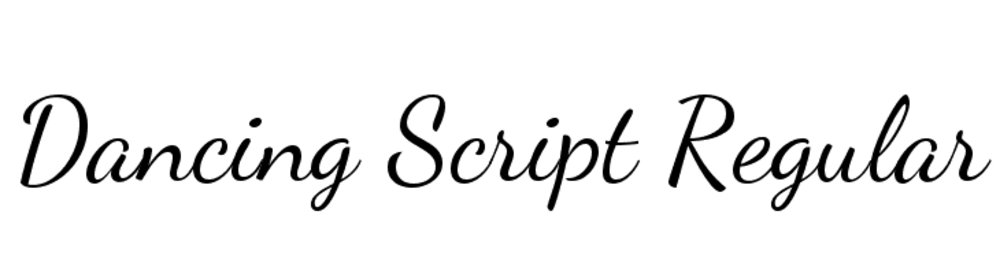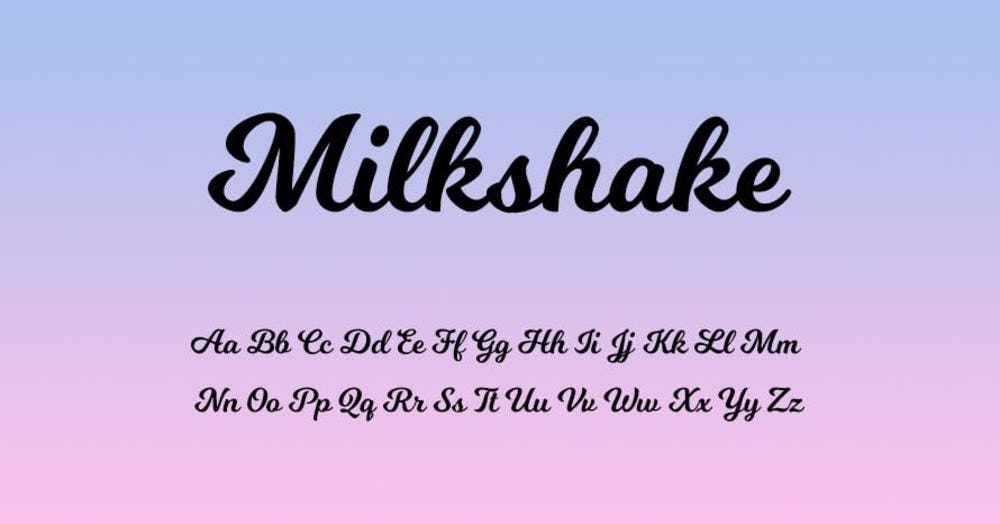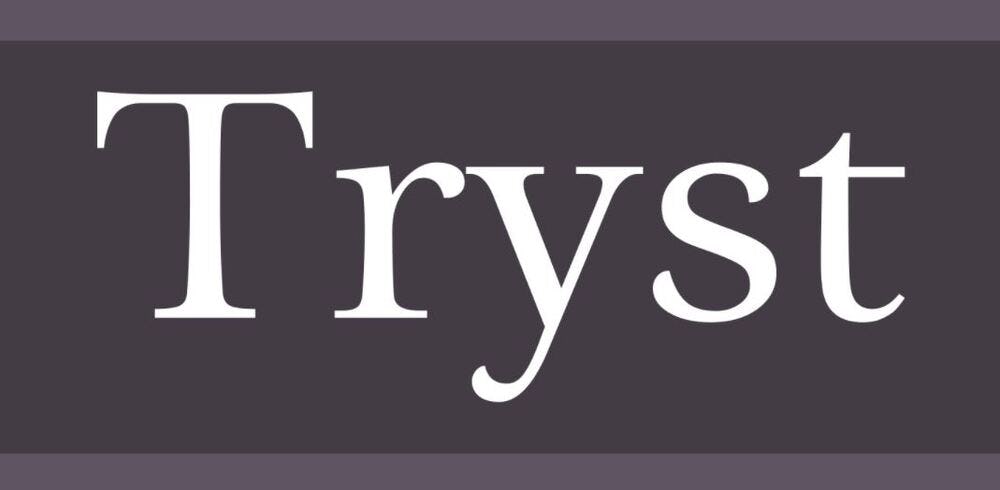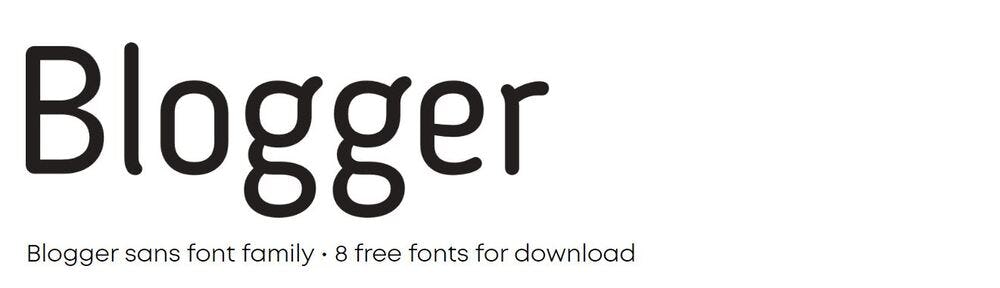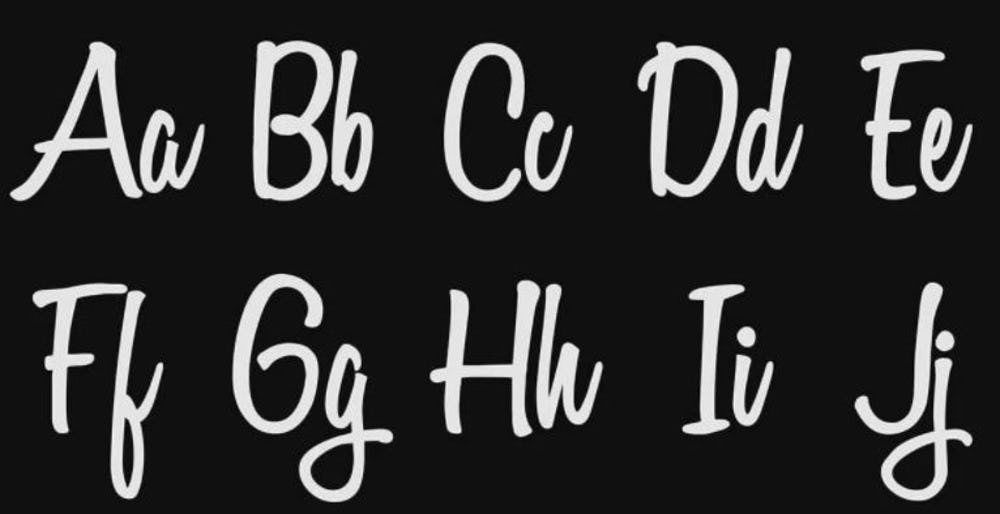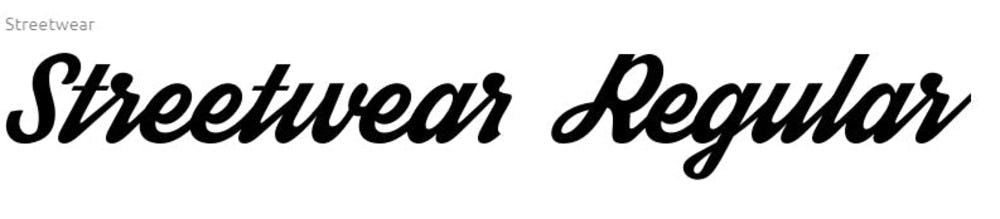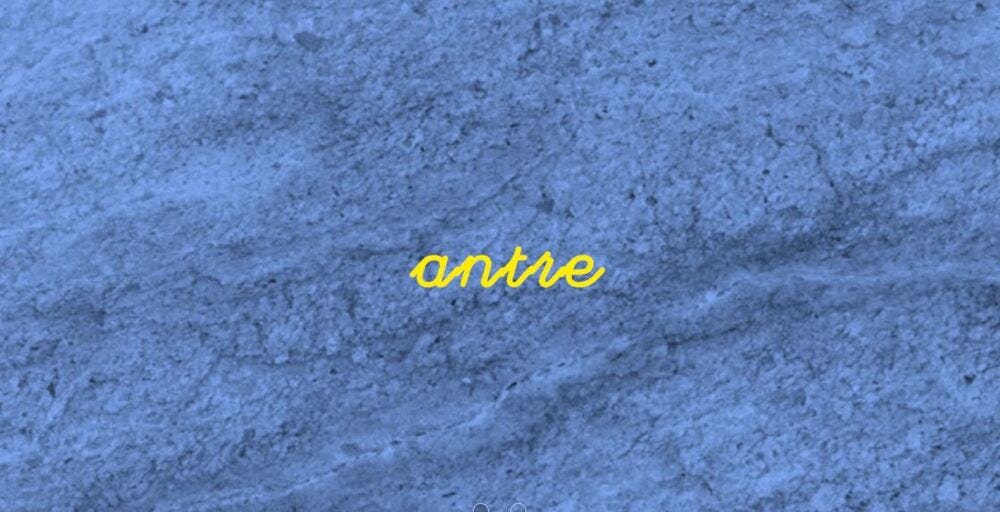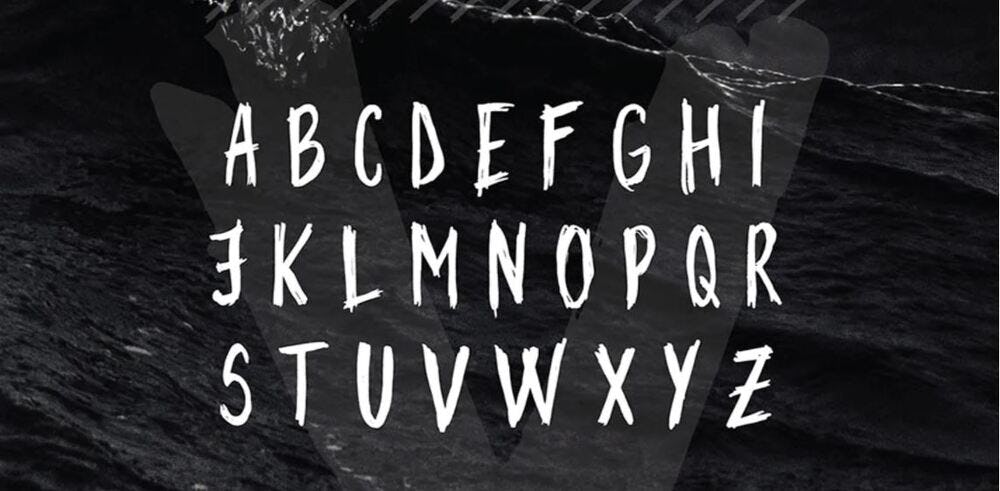
¿Buscas una tipografía para apuntes que te ahorre tiempo y se vea bien? ¿Estás cansado de ver las mismas letras para apuntes en Word o Powerpoint cada vez que haces un proyecto para la universidad o para el trabajo? Si bien al usar la tecnología ya no tenemos problemas para entender nuestras notas, la mayoría de fuentes no suelen ser tan vistosas.
Según la Escuela de la Memoria, organización enfocada en el desarrollo de la memoria de alta competición, la toma de apuntes nos ayuda a recordar mejor la información y estimula nuestras capacidades perceptivas e intelectuales. Sin embargo, por más que sea una actividad muy beneficiosa para ti, no podrás disfrutarla si no te sientes motivado a hacerlo.
Aquí entran en acción las tipografías para apuntes que hemos recopilado para ti, pues cada una hará que te enamores del proceso de tomar notas para que, cuando estés a cargo de la redacción de los puntos claves de algún proyecto o simplemente quieras anotar tu agenda de la semana, disfrutes cada segundo.
Recomendaciones para elegir la tipografía para apuntes ideal
Antes de que puedas descargar todas las tipografías para apuntes que hemos recopilado para ti, queremos compartir contigo algunas pautas que te ayudarán a escoger las fonts para apuntes que más te convienen.
Para ello, debes tener en cuenta que, si vas a utilizar una tipografía para apuntes para elaborar documentos, presentaciones animadas o simplemente para tomar notas, según Hubspot, lo mejor es evitar tipografías que tengan mucho diseño porque pueden confundir a quién tenga que leer el documento.
Si bien a todos nos gusta tener estilo, en la tipografía para apuntes debe primar, antes que nada, la legibilidad. La idea es que entiendas tus apuntes al primer vistazo y no tengas que detenerte para entender qué es lo que escribiste, pues, de lo contrario, tus apuntes perderían su misión principal: ayudarte a ahorrar tiempo.
Pero, tranquilo, esto no quiere decir que tengas que sacrificar tu buen gusto para utilizar letras que sean entendibles. En este artículo, encontrarás tipos de letra para apuntes que mezclan estilo y legibilidad, así que, finalmente, todo dependerá de tus gustos.
Tipografía para apuntes bonitos
Comenzamos nuestra lista de tipografías para apuntes con más de 10 alternativas que te cautivarán al instante por sus formas y estilos. Como te comentamos antes, si bien las letras para apuntes deben ser legibles, esto no quiere decir que deban ser aburridas.
1. Astron
Tipografía para apuntes futuristas
Si te gusta la onda gaming o futurista, este tipo de letra para apuntes es el indicado para ti. Si bien tiene un estilo particular, destaca por su gran legibilidad, así que no es para nada descabellado que las uses en tus notas.
De hecho, le darán un toque mucho más personal a tus documentos y, al captar tu atención fácilmente, pueden ser la tipografía para apuntes más adecuada para resaltar los puntos importantes de un tema en específico.
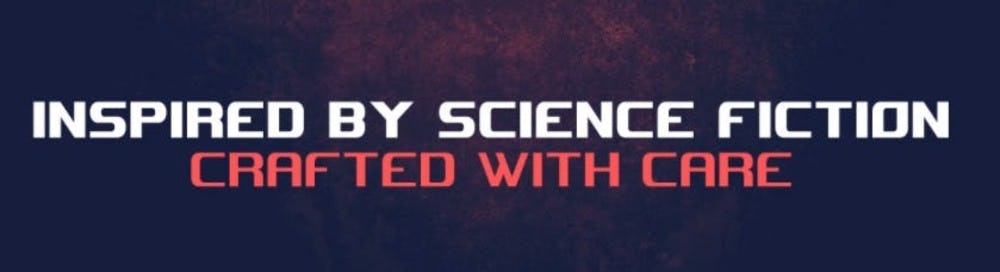
2. Lilly
Una fuente para apuntes de elegancia sútil
Lilly es una tipografía para apuntes con una apariencia extremadamente amigable gracias a sus formas que son muy fáciles de comprender a simple vista.
Puedes encontrar esta fuente para apuntes disponible en mayúsculas, minúsculas, números y signos de puntuación. Además, cuenta con varios estilos, como para que tus notas tengan una gran estructura.
3. Magical Feather
Haz tus apuntes con un toque de magia
Esta tipografía para apuntes es perfecta si quieres elaborar un mapa conceptual, pues las letras no pasarán de ser percibidas. Si te detienes un segundo a analizar sus formas, notarás que es súper natural y que, además, tiene buena legibilidad. Por lo tanto, podrás leer tus apuntes todas las veces que quieras y entenderlos a la perfección.
La fuente para apuntes Magical Feather está disponible en mayúsculas y minúsculas, además de incluir números y signos de puntuación.
4. Ananda
Una fuente con glamour
Si le prestas atención a los detalles, esta tipografía para apuntes te parecerá genial. Ananda destaca por su caligrafía cálida y por sus formas curvas, lo cual aporta una sensación de glamour.
Así que, si quieres apuntes elegantes y legibles, esta tipografía es la que estabas buscando.
5. Coneria Script
Más perfección para tus apuntes
Coneria Script no solo es una tipografía para apuntes que le presta mucha atención a los detalles, sino también un tipo de letra con toques vintage, pues parece que hubiera sido escrita con una pluma.